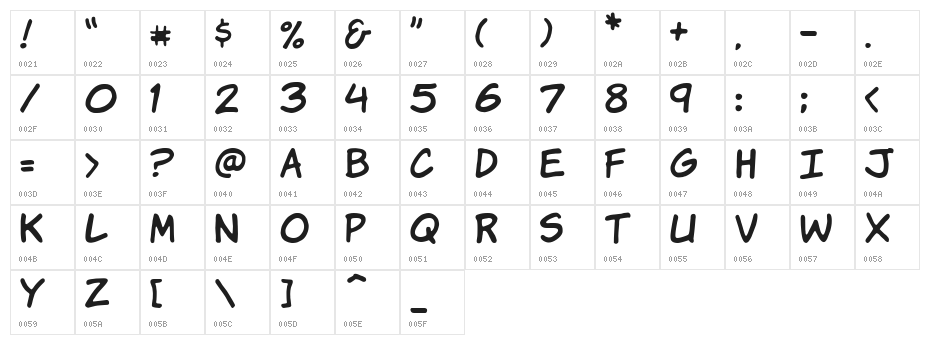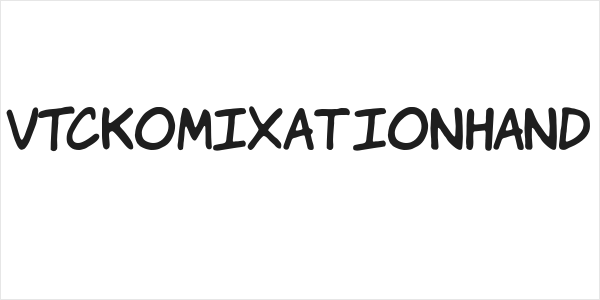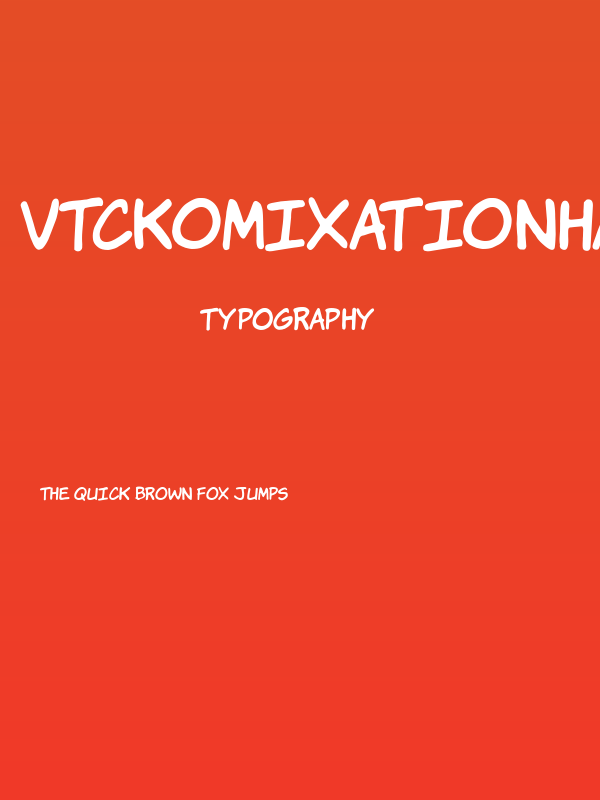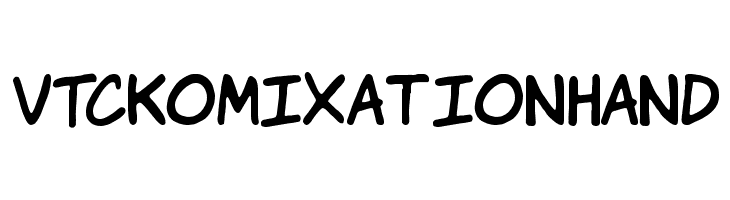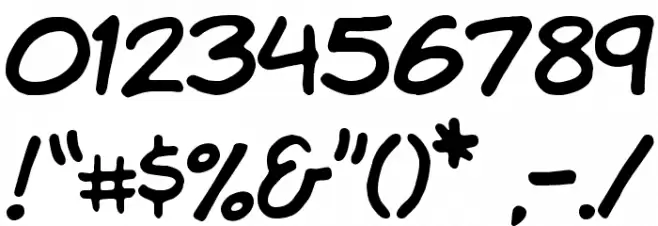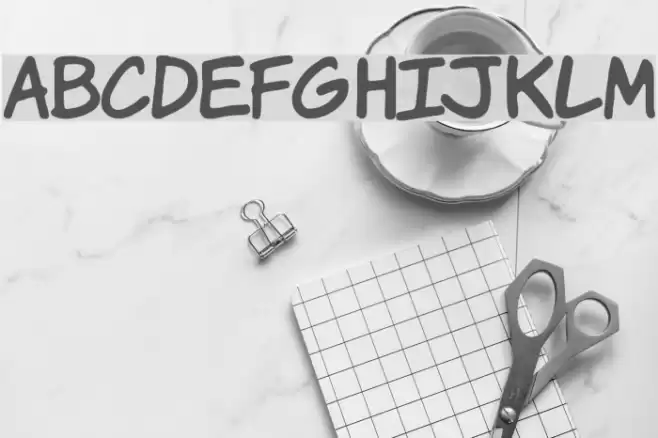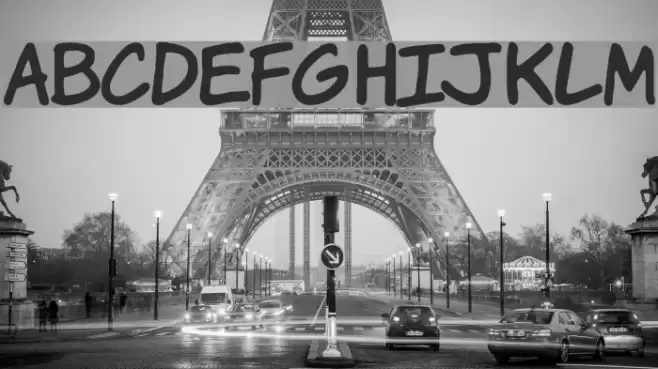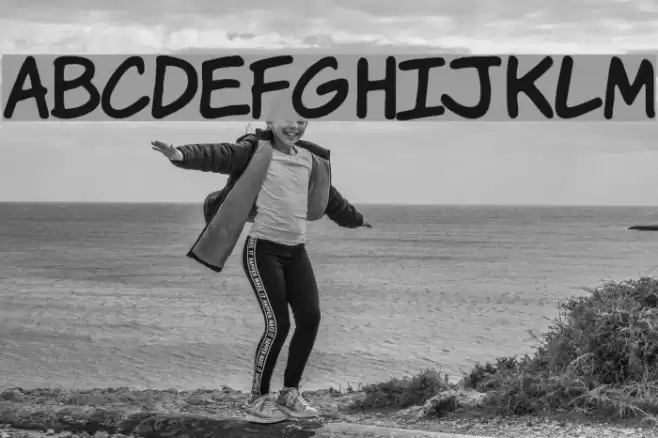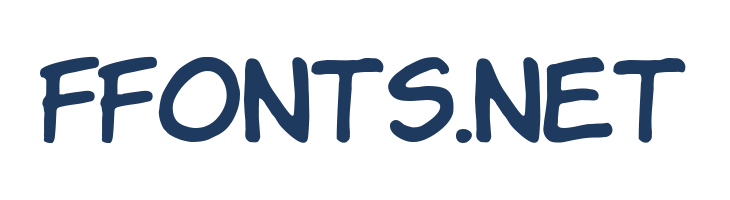
VTCKomixationHand Font
✎ Capitals
| Gesamtstil | Playful |
| Vorgeschlagene Projekte | Ideal for comic books, children's books, playful branding, and informal posters. |